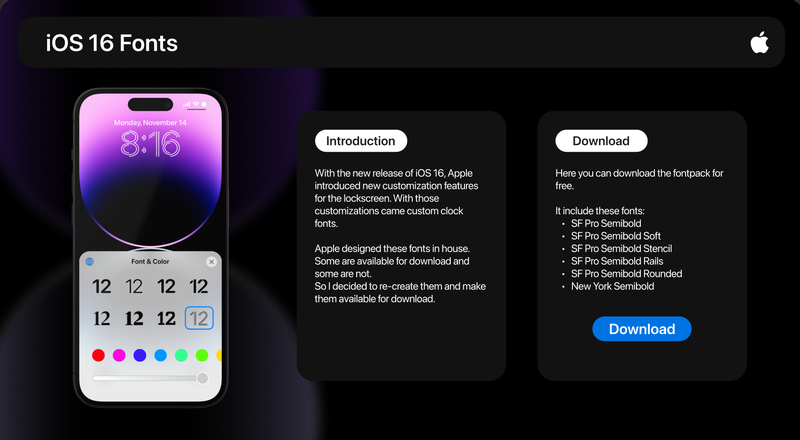
Cách thay đổi font chữ iPhone cho Android để trải nghiệm phong cách mới lạ cho thiết bị của mình
Nếu bạn là người yêu thích phong cách iPhone và muốn mang một chút của iOS vào thiết bị Android của mình thì có thể thử thay đổi font chữ iPhone cho Android. Bằng những thao tác đơn giản, bạn có thể nhanh chóng mang đến cho thiết bị Android của mình một diện mạo mới, giống như iPhone. Trong bài viết này, bạn hãy cùng FPT Shop tìm hiểu về cách thay đổi font chữ iPhone cho Android nhé.
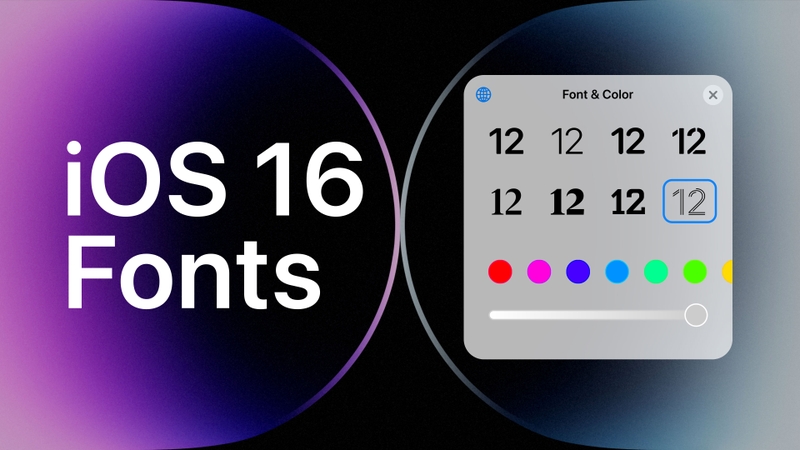
Lý do bạn nên thay đổi font chữ iPhone cho Android
Font chữ là yếu tố quan trọng góp phần tạo nên phong cách và trải nghiệm người dùng trên các thiết bị di động. Mặc dù Android và iPhone có sự khác biệt về giao diện và hệ điều hành, nhưng bạn hoàn toàn có thể mang một phần của iOS lên thiết bị Android của mình. Thay đổi font chữ iPhone cho Android mang đến nhiều lợi ích như:
Làm mới giao diện điện thoại
Nếu bạn đã sử dụng chiếc Android trong một thời gian dài và cảm thấy nhàm chán với giao diện mặc định, thay đổi font chữ là một cách nhanh chóng để làm mới giao diện. Với font chữ iPhone, bạn sẽ có cảm giác như đang sử dụng một thiết bị iOS, mang đến sự mới mẻ và thú vị cho điện thoại của mình.
Tạo phong cách cá nhân riêng biệt
Thay đổi font chữ iPhone không chỉ giúp điện thoại của bạn trông bắt mắt hơn mà còn thể hiện được cá tính riêng của bạn. Chọn một font chữ độc đáo không chỉ thay đổi hình thức mà còn giúp bạn tạo ấn tượng với những người xung quanh.
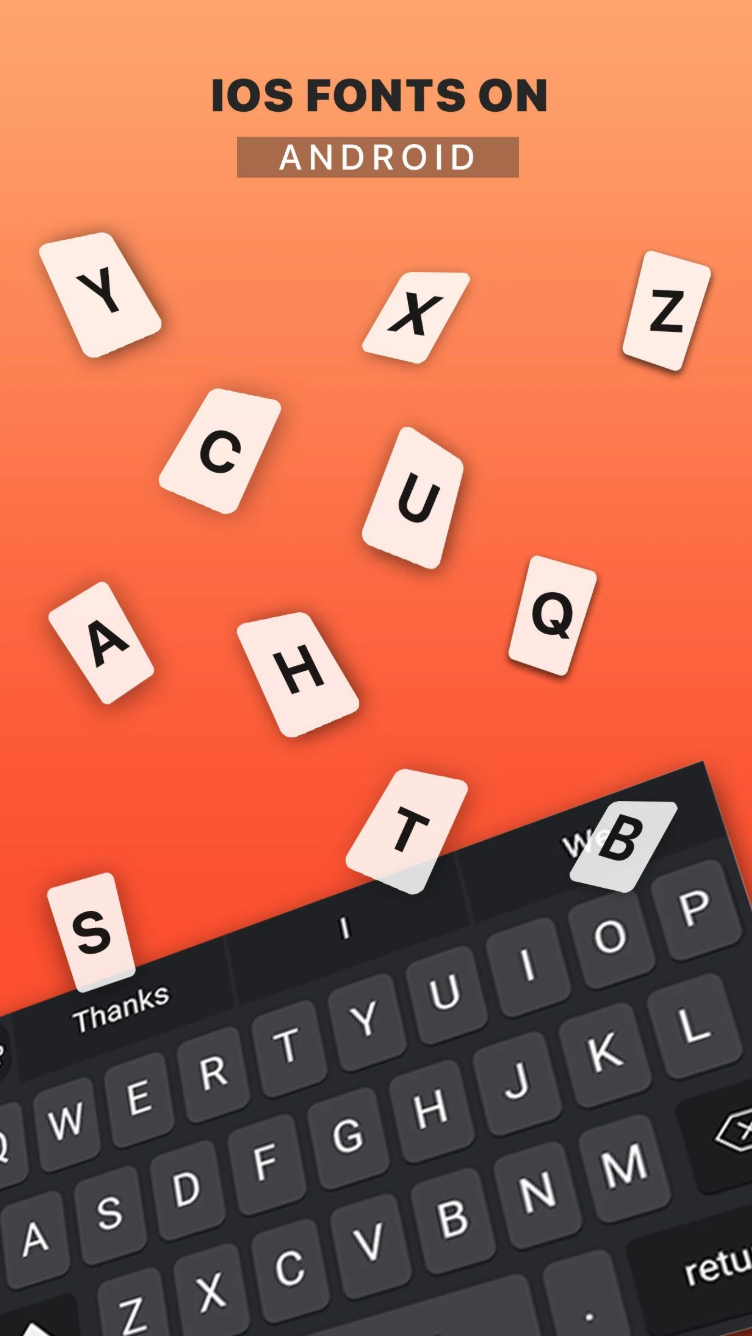
Tăng cường trải nghiệm người dùng
Những font chữ iPhone được thiết kế rất tinh tế và dễ đọc. Sử dụng các kiểu chữ này trên Android sẽ giúp bạn cảm thấy dễ chịu hơn khi đọc văn bản hoặc tương tác với giao diện, đặc biệt trong các ứng dụng hoặc khi gửi tin nhắn.
Cách thay đổi font chữ iPhone cho Android
Sử dụng ứng dụng iOS Font for Android
Một trong những cách đơn giản và hiệu quả nhất để thay đổi font chữ iPhone cho Android là sử dụng ứng dụng iOS Font for Android. Đây là một ứng dụng miễn phí, giúp người dùng Android dễ dàng áp dụng phông chữ iOS cho điện thoại của mình.
Ứng dụng iOS Font for Android còn cho phép bạn thêm các emoji của iOS, mang đến trải nghiệm iOS hoàn chỉnh trên điện thoại Android của bạn.
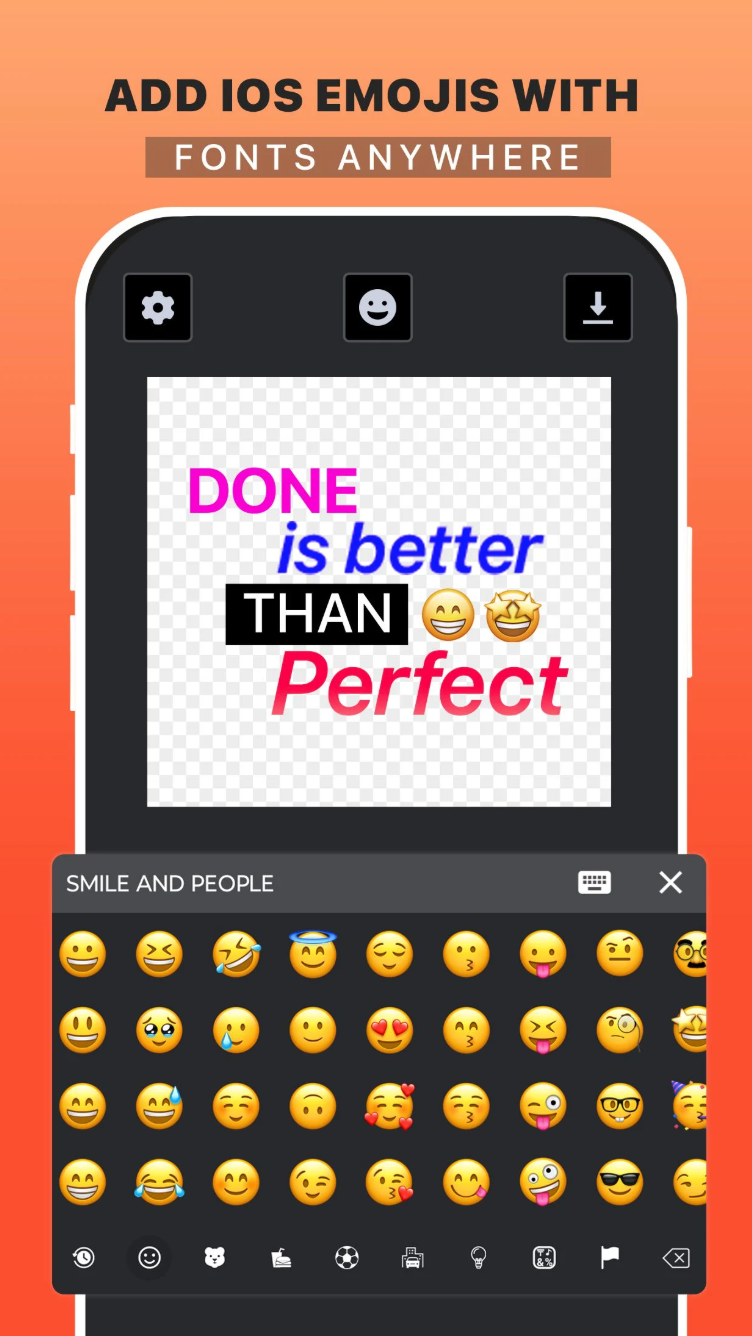
- Bước 4: Sau khi tải và áp dụng, bạn sẽ có ngay một giao diện mới với font chữ giống iPhone.
Sử dụng ứng dụng launcher để thay đổi font chữ
Nếu điện thoại của bạn không hỗ trợ thay đổi font chữ trực tiếp trong cài đặt, bạn có thể sử dụng các ứng dụng launcher như Nova Launcher hoặc Action Launcher. Những ứng dụng này không chỉ mang đến tính năng thay đổi font chữ mà còn cho phép tùy chỉnh giao diện của điện thoại Android.
Cách thực hiện:
- Bước 1: Tải ứng dụng Nova Launcher hoặc Action Launcher từ Google Play Store.
- Bước 2: Mở ứng dụng và vào phần Cài đặt của launcher, chọn mục Hiển thị hoặc Appearance.
- Bước 3: Chọn Font và duyệt qua các kiểu font chữ có sẵn. Sau đó, chọn font iPhone hoặc kiểu font mà bạn thích.
- Bước 4: Áp dụng font và bắt đầu trải nghiệm giao diện mới.
Những lưu ý khi thay đổi font chữ iPhone cho Android
Tính tương thích thiết bị
Không phải tất cả các dòng điện thoại Android đều hỗ trợ thay đổi font chữ theo cách này. Một số dòng máy cũ có thể gặp vấn đề khi tải ứng dụng hoặc áp dụng font chữ mới. Bạn hãy kiểm tra tính tương thích của thiết bị trước khi thực hiện thay đổi.
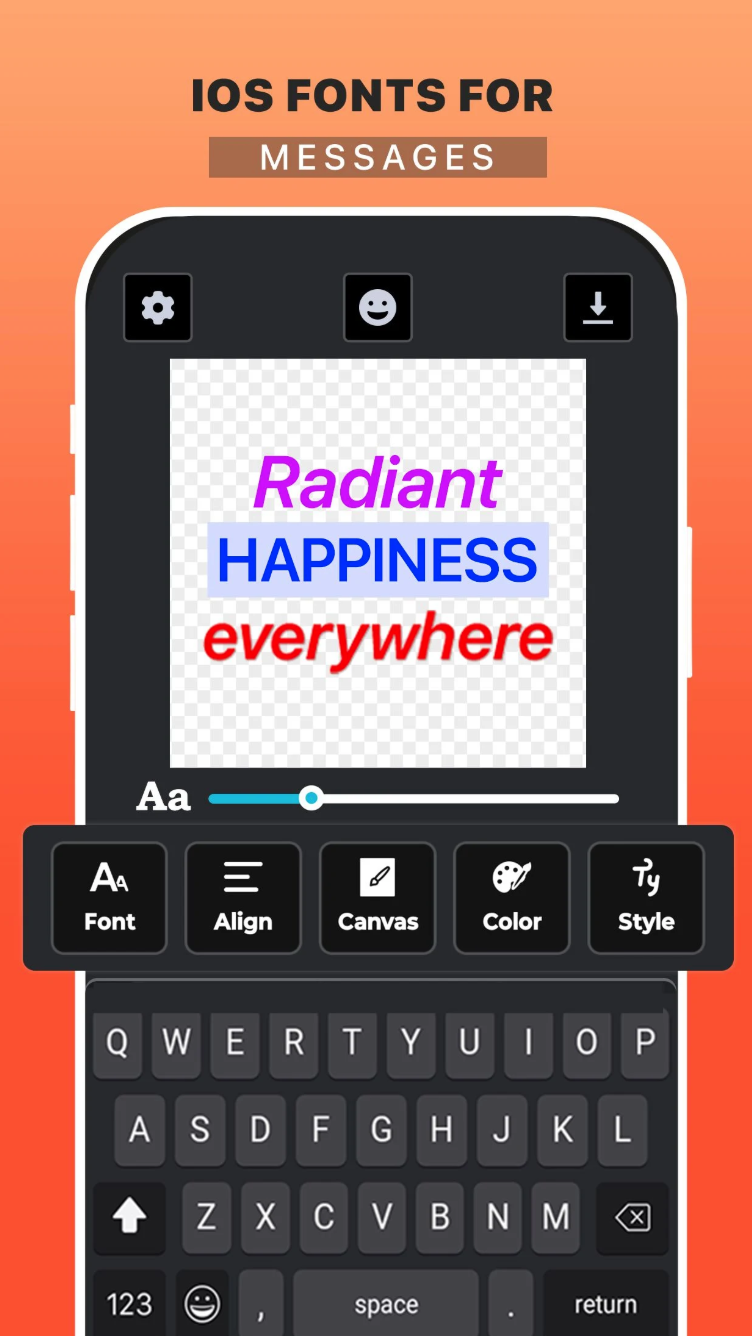
Ảnh hưởng đến hiệu suất
Một số ứng dụng hoặc giao diện có thể bị ảnh hưởng hiệu suất khi thay đổi font chữ, đặc biệt nếu bạn sử dụng font chữ có quá nhiều kiểu dáng phức tạp. Điều này có thể làm chậm tốc độ hoạt động của điện thoại, vì vậy hãy chọn font chữ nhẹ và dễ sử dụng.